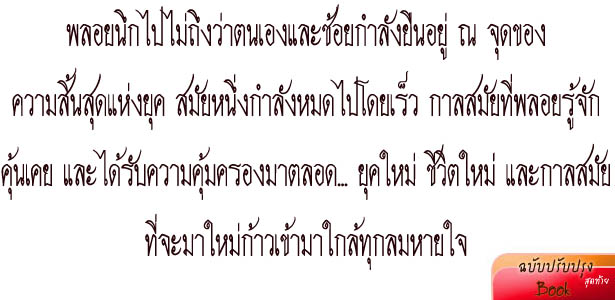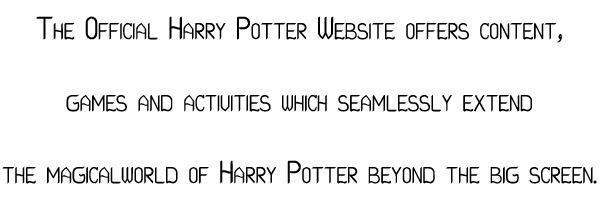
ครับ แล้วจะพยายามแก้ครับ
ช่วงเดือนที่ผมหายไปนี่ มีฟอนต์ใหม่ๆ แปลกๆ และฝีมือดีๆ (กว่าของผมทั้งนั้น) เรียงรายมาให้ดูกันใหญ่เลยครับ
ก่อนอื่นเวลาทำภาพตัวอย่างอยากให้คุณบุ๊คลองเซฟมาเป็น .gif หรือ .png (ตั้งระดับสีไว้ 8 บิต หรือ 256 สีก็ได้ครับ)
มันจะทำให้ขอบภาพดูคมและไม่ย้วยเละแบบที่ JPG เป็น
ฟอนต์ของคุณสวยมากๆ ครับ ไม่รู้ว่าวันนึงผมจะทำแนวนี้ดูไหวไหม
ถ้าจะตั้งข้อสังเกตก็มี
- ตัว ม ขมวดล่างของม้า อยากให้สุงกว่านี้หน่อยครับ จะได้ไม่ดูเตี้ยผิดส่วน (ลองพิมพ์ มนุษย์นมมนต์)
- สระอือ เท่าที่เห็น ฟันหนูมันชิดกันครับ เลยรวมกันเป็นก้อนเดียว
- ไม้โท หางของมันน่าจะไปกันได้กับ ช หรือ ส ลองดัดดูนิดนึงครับ จะได้ไม่ตีกัน
- หัวของไม้โทก็เล็กกว่าตัวอื่น เลยดูตัน ลองปรับให้โปร่งอีกนิ๊ดครับ
- เรื่องช่องไฟหน้าสระไอ ใด โอ เดี๋ยวไว้ค่อยคุยกันเรื่อง Kerning ครับ (แต่ปรับดึงเข้ามาหน่อยก็ดี)
ทำตัวอักษรภาษาอังกฤษด้วยรึเปล่าคะ อยากเห็นจัง
ฟอนต์ตัวนี้ผมปรับมาจะนับไม่ถ้วนครั้งแล้วครับ แต่ก็กะว่าจะแก้ให้ถูกใจทุกคนก่อนปล่อย (ประกอบกับขี้เกียจทำแฟลช และฝีมือแฟลชข้าพเจ้าห่วยมาก :08:)
โทษที เมื่อกี้ลืมโพสต์รูป
อันนี้ให้พี่วาฬ เป็นฟอนต์อังกฤษที่สิ้นคิดที่สุดในโลก
ตัวอังกฤษมันดูแข็งๆนะ
ลองพิมพ์พร้อมกับตัวภาษาไทยดู อาจจะเข้ากันก็ได้มั้ง
แล้ว-- มีภาพพรีวิวไหมเอ่ย
ตอนนี้มีแต่อันเล็ก
ฟ้อนต์สวยดีอ่า
ชอบๆๆ
สวยมากครับ